字体设计在变化之前,你得先做这一步
不知道大家有没有遇到过这样一种情况,我们在做字的时候,发现做好的两个字死活搭不到一块,明明字分开看都没有问题,可是放在一起就感觉不太对。如果我们做的字出现了这种不搭的情况,肯定是因为字与字之间存在着不同。今天的这节课,我们给大家讲解一下,如何让你做的字体看起来更和谐。
想要解决这种不搭的问题,我们可以从两方面下手。第一个就是减少字与字之间的不同之处,第二个则是增加文字之间的相同之处,去掩盖字的不同。我们先从治标又治本的减少不同开始讲。
我们先来看下这四个字,可能乍一看会觉得没啥问题,可是我们仔细盯着会发现其实这四个字根本不搭。欢字比乐字大了许多,今字的重心又要比宵字低许多。为什么会出现这种情况呢?我们把这四个字分开看,他们也并没有什么太大的问题。
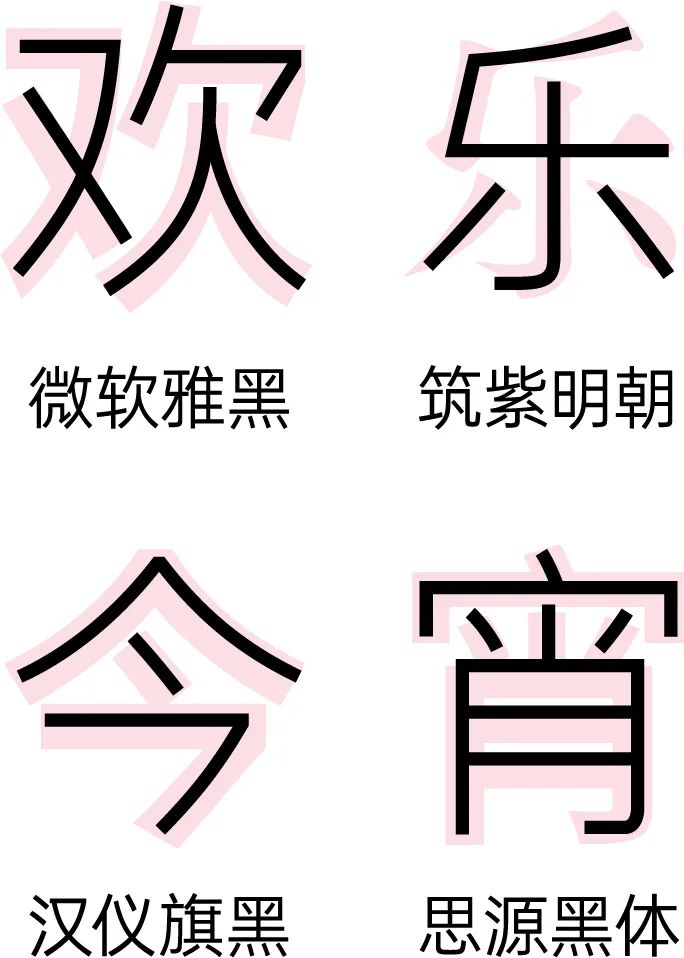
其实这四个字是我分别用了四个字库字体修改的,刨除了他们的体饰之后,我们会发现他们的骨骼区别是很大的,也正是因为他们骨骼上的不同,导致了这四个字看起来不搭。所以我们要减少不同,首先就从骨骼开始讲。
其实这方面的知识我在“字体设计第一课”的那节课已经讲过一部分了,如果没看过那节课的同学建议你先停下来,去补一补那节课的知识哦。而看过的同学就跟着我一起往下听。我们依旧分别从中宫、重心、字面和灰度四方面来讲解,先来看看中宫。
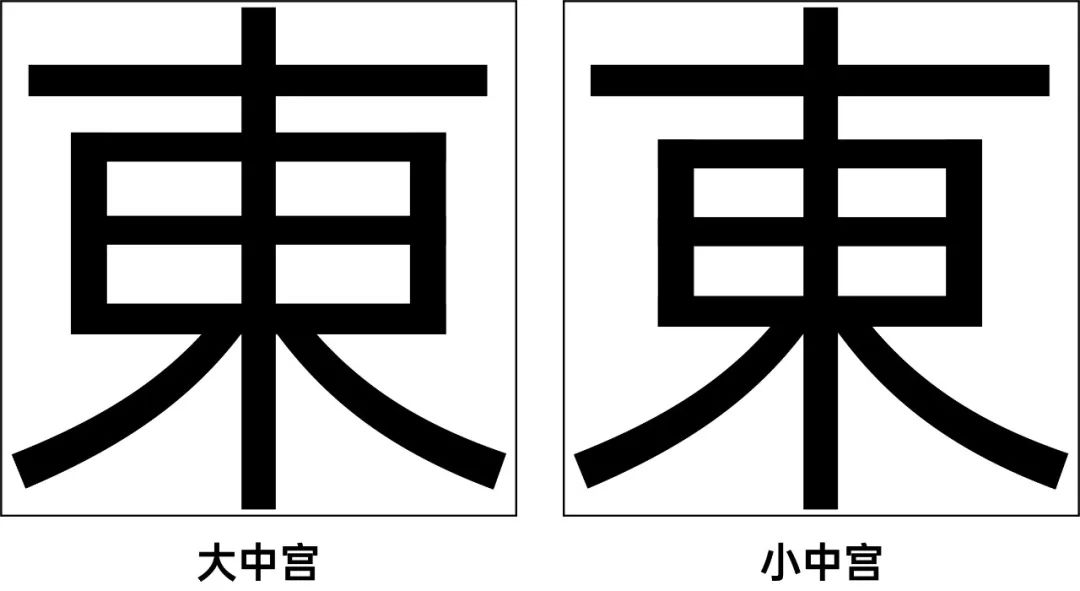
从视觉上来说,中宫大的字会更多的占据字面框,看上去也会显得比较大一些,而中宫小的则显小,这也是为什么中宫不同的字放在一起会显得不搭。
来看个实际的例子,现在画面中重塑的这两个字是不是感觉不太搭?这里我们可以通过字面框内字体外侧的负空间去判断中宫的大小,我们在底下叠一个字面框,就可以发现重字的四周还是有一些负空间,而塑字则几乎占满了字面框,所以他们的中宫的差距是比较大的,导致了视觉上的大小不一致。
我们分别调整一下这两个字,调整中宫之后的他们就舒适多了。
接着来讲一下重心,重心不一致除了会让文字看起来不搭之外,重心的频繁上下跳动也会让阅读更加的疲劳。屏幕上马赛克这三个字重心就非常的不一致,马字重心在中间,赛字重心偏低,而克字偏高。
经过调整之后,这三个字也就更和谐了。
然后是字面,我们在字体设计第一课中用过这四种图形去类比成四种外轮廓不一致的文字。如果将他们上下端物理对齐的话,他们在视觉上其实是不平衡的。所以得对他们进行一些视觉上的修正,适当地调节他们的字面。
除此之外,这里再补充一个新的知识点,就是笔画多的字需要放大一些,笔画少的字需要缩小一些。例如画面中椅子这两个字,子字看着要比椅字大了许多,可是他们的字面大小是完全相同的。将子字缩小一些之后才显得大小比较一致。
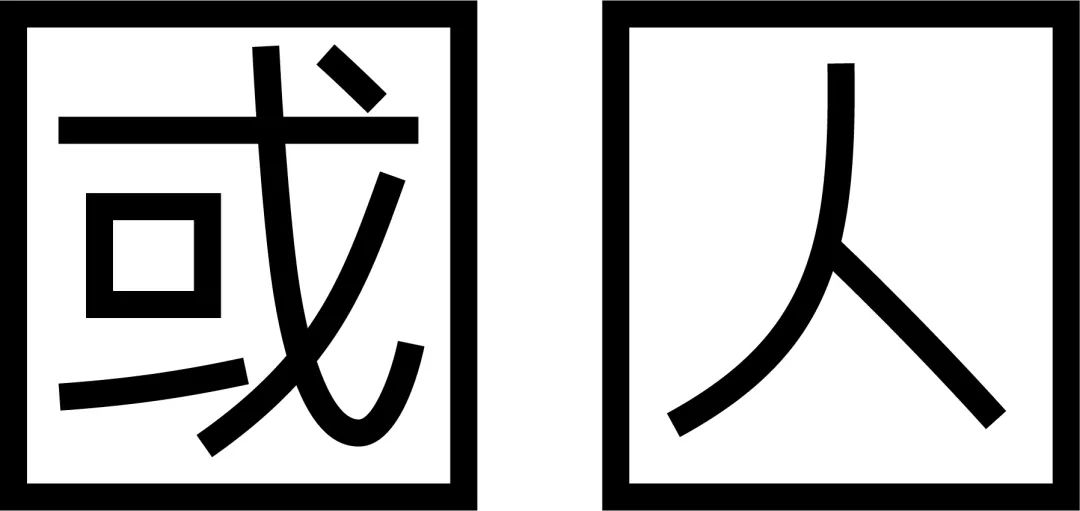
举一个更加直观的例子,画面中繁体字的国字看上去要比囚字小一些,可是其实这两个字的外轮廓无论是大小还是形状都是完全一致的。
最后回顾一下灰度,灰度主要指的是对于笔画少的字,笔画应该相对应的粗一点,笔画多的字,笔画则应该细一些。现在画面中的士字就是与另外两个字差不多粗细的,可是在视觉上士字明显是要偏细的,看上去显得特别弱。所以要将士字加粗一些,让字体之间的灰度差距别太大。
除此之外,日本字体设计师成泽正信提出过一个理论,他说对于首尾两字都是笔画特别少的词组,那么首尾的这两个字需要在已经视觉加粗过后的基础上,再加粗一些,不然词组会显得有些无力。
关于骨骼的内容我们就讲到这里,也许你们会觉得这么多需要微调的地方很难记。那么这里我再给大家介绍一条总结前面内容的定律。古希腊的智者普罗泰戈拉说过一句话叫“人是万物的尺度。”这句话或许是错误的哲学观点,可是在设计中却是一句真理。
用通俗点的话就是眼睛才是最准确的衡量标准。因为我们很难总结出笔画少的字要比笔画多的字小多少,笔画得粗多少。视觉上的调整是难以量化的。所以最简单的方式就是用眼睛去判断,看着细了就加粗,看着小了就放大。
不过我们也需要尊重每一个汉字的不同,没有必要把不同的文字强行调成一模一样,所有字都一模一样,那么字也就不再是字了。汉字不同于西文,可以均匀地分布。汉字天生就是有笔画多少的区分,有重心的高低,有外轮廓的不同,所以汉字在阅读的时候也能产生西文不具备的节奏感,这或许也是汉字的魅力所在。所以我们在做字的时候,追求的是文字之间的和谐,而非绝对一致。
前面我们讲的主要是骨骼上视觉的不搭,接下来我们来分析一下骨骼上气质的不搭。
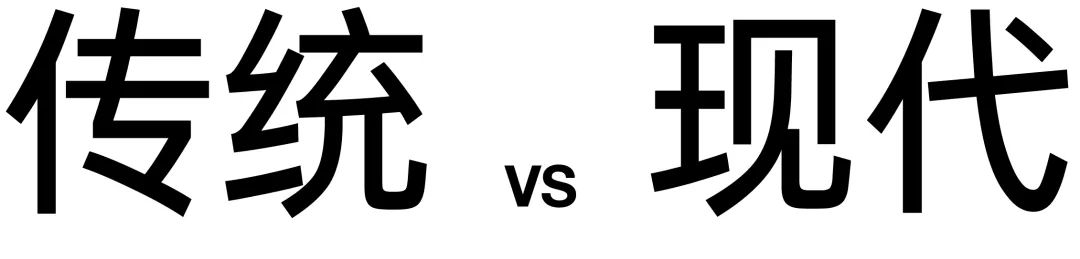
文字的气质最常见的是传统气质和现代气质。
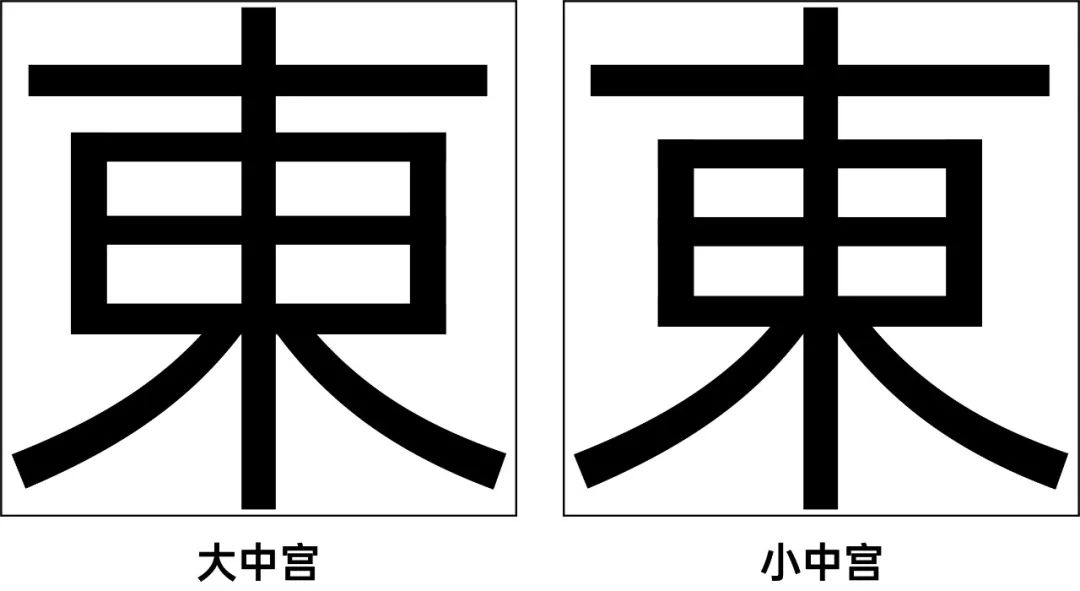
对于传统和现代这两种气质来讲,影响最大的是中宫。刚刚我们展示的这两个東字除了视觉上大小不一之外,他们气质也是相悖的。可是为什么中宫大的会具有现代感,而中宫小的会具有传统感呢?
那是因为在西文的字体设计中,他们更注重文字内部的负空间均匀分布,外部的负空间则可以通过字间距进行调节。
而中文中由于有字面框的存在,在设计字体时需要考虑内白和外白的均衡。所以受到西方设计影响的现代型汉字也会更注重内白的分布,而忽略外白,从而导致了中宫偏大。传统型的字体关注了文字的外白,所以中宫就会偏小一些了。
另一方面,由于最初的印刷技术和电子显示技术不佳,而中宫比较大的字体具有更良好的识别度,所以电脑、书籍、报刊等普遍用的都是中宫比较大的字体。而电脑、书报等正是当时具备现代感的代表物品,所以中宫大的字体也获得了现代感的这种印象。
除了中宫之外,还有笔画的分布。传统型字体保留书法中的左收右放、上紧下松的特点,而现代字体则讲究的是视觉上的均衡分布。
来看看这两个林字,左边的是传统的,我们可以很明显地看到左边的木字要小于右边的。而右边现代一些的林字,为了让视觉上比较平衡,左边的木字微微地比右边的小一点点;另外右边的林字重心是在视觉中心上的,而左边的则要更偏上一些。
骨骼分析完了,接下来我们来分析一下笔画。
首先要统一好笔画的线条,我们来看这两个撇笔画,他们的曲线就是两种不同的风格。
来看左边的这个,这个笔画其实是我从颜真卿写的木字中提取出来的,所以他的线条是具备有手写感的。
然后要注意笔画的起笔收笔是否统一,例如画面中的这三个字,分别是圆头的、平头的,以及对笔画末端进行切笔的。
笔画的体饰相信大家都知道需要统一,体饰不同的文字看上去就完全是两个字体了。
然后是笔画的粗细比例。例如画面中的这两个字虽然中宫、重心、字面和灰度都是一样的,可是横竖笔画的粗细比例不同,所以他们也明显搭不到一块去。
最后是笔画转折处需要统一,拐角处是用尖角还是圆角,又或者是规定某一个方向的拐角做特殊处理。
笔画上的细节可远不止我提出来的这五点,比如还有装饰角出现的位置、拐角的大小、曲线等等。虽然这些都是非常非常小的细节,可是小细节累积起来就成了大问题了,只有将这些隐藏在笔画里的小细节都统一了,我们做的字看起来才能够比较和谐美观。
当我们尽可能地将文字中的不同之处消灭之后,那么我们就可以进入下一步,增加文字之间的共性了。那么增加共性到底是个怎么样的东西呢?
日本著名字体设计师高桥善丸总结过一个理论——做字之前需要找到文字之间的视觉关联性,然后强调其中的特征。这里说的视觉关联性也就是我们所说的共性,强调共性不但可以让文字之间看起来更和谐,同时也能让字体产生表现力。接着来看一下我们可以从哪些方面去寻找共性。
这里我总结了寻找共性的三个方面,分别是笔画、偏旁或结构和骨骼。
先来看看笔画,笔画里我又细分出了四个点。
首先是统一笔画的弯曲程度,一般最常见的是将曲线笔画改成直线笔画。因为在中文中存在着横、竖等直线笔画和撇、捺等曲线笔画,而不同字的直线笔画和曲线笔画的数量不同,如果我们将所有的笔画都转变为直线的话,那么文字的共性也能得到增加。
来看一些实际的例子,崩坏这两个字,崩字的曲线笔画是比较少的,而坏的繁体字则存在着比较多的曲线。而这位作者将笔画尽可能直线化之后,这两个字也产生了强烈的共性。
这个是高桥善丸的字体作品,野放途这三个字也是全部用直线构成的,所以他们看起来是非常和谐的,另外高桥善丸为了体现野放途的那种自由奔放的感觉,还随意地将部分笔画进行了延长。
当然我们也可以将笔画尽量的曲线化,但是这样的难度是要比直线化大许多。这依然是高桥善丸的作品,水都这两个字都尽量地曲线化去展现水的特质,高桥善丸还将这两个字处理成圆形去增加他们之间的共性。
这个字体作品就曲线化的更彻底了,包含横、竖在内的所有的笔画都是由曲线构成的。
刚刚讲到将曲线变为直线,其实我们还可以进一步将笔画的倾斜角度给统一了,这样文字的统一程度就更高了。
来看看这个字体作品。这四个字的笔画只用了四个倾斜角度。分别是垂直的竖画、倾斜14°的横画、倾斜63°和-63°的撇、捺、点等倾斜笔画。
第三点是设计特征笔画,也就是我们可以选择词组中大多数字都共同拥有的笔画,然后对他进行比较有个性的设计。最常见的就是将点笔画设计成圆。
河童这两个字就是将笔画中的点都处理成了小圆圈。
有时候我们也能根据词义将小圆圈变成别的点形状,例如井上悠的这个作品,为了突出雨的概念,将笔画点都替换成了蓝色的小水滴。
除了点之外,别的笔画也可以用这样的手法。例如这组字,撇和捺笔画的设计都是比较醒目和夸张的。
最后一点是在字体中加入书写笔画,这个手法适用范围是比较广的。例如画面中这个a piece of 工作室的作品,他在书法的宋体字中加入了日文的平假名,而日文的平假名来源于草书,我们也可以看做是加入书法笔画。
说了这么多,是时候来个案例的演示了。我们来做离骚这两个字。因为离骚是历史上的文学著作,具有强烈的文化属性,所以希望把他做成宋体字。
宋体字应该从横画开始做起,这个便是设计好的横画,从他体饰的曲线可以看出来,这是一款传统型的宋体字。
接着我们可以从横画推导出其他的笔画,具体怎么推导我们在《设计宋体字很难,这次我来教会你》的那节课中有详细的讲解,不懂的同学可以去翻看一下。
接着我们来选择一个参考字形,因为我们的定位是传统型的宋体,中宫必须也得相应小一些,所以我选择了筑紫明朝的老字形。
我们在参考字体的骨骼上把设计好的笔画填上去,由于筑紫A老明朝是偏手写风格的宋体,所以不同字的字面并不一定完全一致,离骚这两个字就明显的大小不同,而我们这节课追求的是文字之间的和谐,所以我们还是尽可能地让这两个字差不多大小。
所以我们将离字给改大一些。
然后我们就要在这个字里寻找替代成书法笔画的地方。我们替换书法笔画可不是随便找一个笔画就替换的,一方面,他必须要在字里占据比较明显的位置,如果在边边角角不显眼的位置进行替换的话,那几乎就等于没有替换;另一方面是这个笔画要符合书写的走势,要能够展示书写笔画的美感。所以我们这里选择了将这两处替换成书法笔画。
我们将设计好的书写笔画替换上去,那么这个字就做好啦。
接着是偏旁或者结构的部分,这个部分我分成了笔画、偏旁和结构。
也许你们会觉得奇怪,为什么刚刚有专门讲笔画的部分,而在偏旁结构这个部分也有笔画呢?我们用反叛这两个字来做例子解释一下。这两个字一共有五个撇笔画。而在字的最左端各有一个撇笔画,我们可以针对这两撇做特殊处理。所以我们这里强调的笔画是有位置上的关系的,而不是指相同的笔画。我们开始处理这两个字。
同样选择一个参考字形,刚刚我们做的是具有传统气质的宋体,那么我们这个字就做具有现代感的大中宫字体,所以我选择了用中宫比较大的微软雅黑作为参考。
因为反叛这个词带有不走寻常路的意味,而一般的字体设计都是横细竖粗的,所以我们对反叛这个词设置成横粗竖细,具体粗细比例暂定为1:2.5。然后将文字搭建起来。
由于两个字的笔画数量不同,使用一样的粗细比例的话会导致灰度上的不均匀。所以这里我们可以适当地调整一下笔画的粗细,让两个字的灰度别相差太远。
接着我们要强调一下这两个笔画。我们可以将他们加粗,并且往外延伸一些。
可是往外延伸之后,这个反字会显得有些不稳,感觉左下角重了。为了让反字平衡一些,所以我们可以将上面的一横往外伸出一些。
现在的这两个字显得有一些些瘦高,气质有点不太对,所以我们可以稍微往下压一些。
最后调整一些细节,我们这个字就做好了。
我们再来看一个例子,破坏这两个字最明显的笔画分别是撇和捺,他们在这两个字中是属于对称的位置关系,所以我们选择强调的笔画并不一定是要在相同的位置,也可以是对称的位置。
接着是强调偏旁。强调偏旁很好理解,就是如果我们设计的字里有相同的偏旁的话,那么我们就可以将设计的重心放在偏旁上,这样可以保证词组之间的相似性。这里我们用海浪这次词作为例子,参考字形用的是opposans的常规字重。然后在参考骨骼的基础上把笔画搭建好。
首先看海字的这个地方,笔画分布得不够均匀,显得结构有些不稳,所以我们要把海字的笔画调整一下。
接着来看浪字,浪字头上的这个点非常奇怪,像独角兽的角似的。我们将点与底下的笔画分开会显得比较舒服一些。
然后我们就要思考一下三点水应该怎么设计。在找三点水的经典碑帖时,我看到了柳公权对三点水是这么处理的,我觉得可以借鉴到我的这个字中。
那么我就可以将下方的点拉长,做一个转折的处理,这样三点水就成了这两个字里比较突出的设计了。
接着我们可以将这里进行出头处理。让这两个字多一些细节。
最后调整一些细节,那么这两个字就做好了。
同样再来看个例子,柠檬这两个字都是木字旁的,所以作者便对这个木字旁做了往外延长的处理,另外值得注意的是,由于他做的木字旁比较夸张,所以对文字右边的部分也进行了相应的处理,不然左右两边就会被割裂开了。
最后是结构,结构指的是强化文字中具有相同结构的部分。例如味道这两字,他们都有口字的结构,所以我们可以尝试在这上面下些功夫。
味道这两个字我第一反应是联想到热腾腾的美食,是温暖有温度的,所以我在笔画的设计上模仿了宋体横画的体饰,让这个字体有一些人文的感觉。
参考字形选择了中宫偏小的筑紫明朝,筑紫明朝相比我们前面用的筑紫A老明朝气质上会稍微没那么传统。根据筑紫明朝的骨骼将笔画放上去。
这时候会发现这一块的负空间有一点大,而我们希望这个字笔画的分布能够更匀称一些。所以将这一点往下挪一些。
然后这个位置笔画似连非连是字体设计中不应该出现的,将这一点往上收一收。
味字的这一笔也可以往上提一些,让他更符合这一撇的走势。
最后调整一些细节。
然后我们要开始想办法修饰一下这个口字结构,我们在书写的时候经常会有这样的连笔,例如这是王羲之写的口字。所以我们也可以将这个书写结构用在我们的字里,让我们这个字有些书写味道。
我们的这两个字就做好了。
睡眠欲的这三个字同样是对口字结构做了特殊设计,所有的口字结构都处理成开口或者是封闭的圆形。
而今生的这两个字所选取的部分就更加刁钻了,我们可以看到这两个字的上方都有一条绕了一个小圈的曲线。而今生原本的写法并不会产生这样的曲线,所以这位设计师的处理手法也是颇为巧妙。
不过在我们做字功底还不够深厚的时候,最好不要将一些不一样的笔画结构强行处理成一样,这样很可能会破坏掉原本的骨骼,损失了汉字原本的美感不说,还很可能让文字丢失了识别性,那样的字体设计可就得不偿失了。毕竟我们要寻找的是文字之间的共性,而不是将文字的不同强行扭转成共性。那么我们接着来往下看。
最后一个方面就是骨骼的共性了,骨骼我细分成了四点——横画对齐、中宫、重心、字面。其中,除了横画对齐之外,中宫、重心、字面这三个处理方法几乎可以应用于所有的汉字中。
我们先来看看横画对齐。我们在看日本的字体设计时,经常能看到東京这两个字被做成这样的处理。因为東京两个字在结构上是有高度的相似性,所以可以将文字的横画对齐,这样文字就能有比较高的统一性了。
千差万别这几个字虽然被设计得十分的夸张,但是通过将所有的横画进行对齐,让字与字之间产生了共性,所以这样一组个性强烈的字放在一起却不会违和。
再来看看住宅作家这四个字,通过画横线我们可以看到,大多数的横线都对齐了,可是住字中间的一条横线却没有对齐。所以其实我们在用这种手法的时候,也不是一定要所有的横画都对齐才行,只要尽可能将能对齐的都对齐,那也能够产生共性。如果强行对齐会破坏文字的美感或者识别度,那我们就放弃那个难以对齐的横画就好了。
第二点中宫,就是我们可以给需要设计的字体设置一个比较夸张的中宫,让读者一看就被夸张的中宫所吸引。我们用一直往南做个小示范。
我们将一直往南这四个字的中宫尽量地撑大,他们之间就能产生共性,如果我们在底下垫个字面框的话,就可以发现除了一之外的三个字都几乎将字面框占满了。
这个是高桥善丸挺著名的一个作品, 他就将白南风和青雨这五个字的中宫扩得非常大,而中间的笔画都缩得很小,从而形成了图形感。
重心与中宫相同,就是给文字设置一个比较夸张的重心。这组字就是将重心都提得非常的高,让文字在体现张力的同时,又能保持和谐统一。
最后就是设置字面,也就是我们常见的宽体、窄体等。我们用验伤这两个字来示范一下,由于验伤是一首抒情歌曲,具有一定的文艺属性,比较适合秀丽一些的气质,笔画也应该比较细一些,所以这里选用opposans Light字重作为参考字形。
另外窄体相比宽体更具有秀丽、文艺的气质,所以这里我直接将字体压扁作为参考。然后将笔画填上参考字形中。
这时候我们可以发现这两个字视觉上的大小不一致,底部与顶部并不对齐,需要进行一定的视觉修正。
还有验字比伤字看着要宽一些。
将验字缩窄了一些,这样这两个字在视觉上就是平衡的了。
我们在之前的课程里介绍过,重心偏高的字体会更秀丽一些,所以我们也可以尝试将重心往上提一提。
可是重心提高之后,这里的点笔画显得有些太长了,不太美观。所以我们可以将点上下交错着排列,这样可以让点稍微短一些。
接着来处理这个地方,这里负空间大了一些。我们可以将提笔画倾斜一些,多占据一些负空间。
最后调整一些笔画细节,我们这组字就做好了。
这节课的内容到这里就讲完了,我们来回顾一下今天的内容。这节课我们讲的是如何设计出和谐统一的文字,为此我们将这节课分成了两部分,一部分是减少文字之间的不同,另一部分是增加文字之间的共性。减少不同部分我们可以从骨骼、气质和笔画风格三个方面去寻找文字之间不和谐的地方,并把他们修正。而增加文字共性则可以从笔画、偏旁部首或者骨骼三个方面去强调他们的视觉关联性,从而使文字在和谐统一的基础上产生视觉张力。希望这节课的内容能对你们有所帮助,我是千树,我们下期再见。